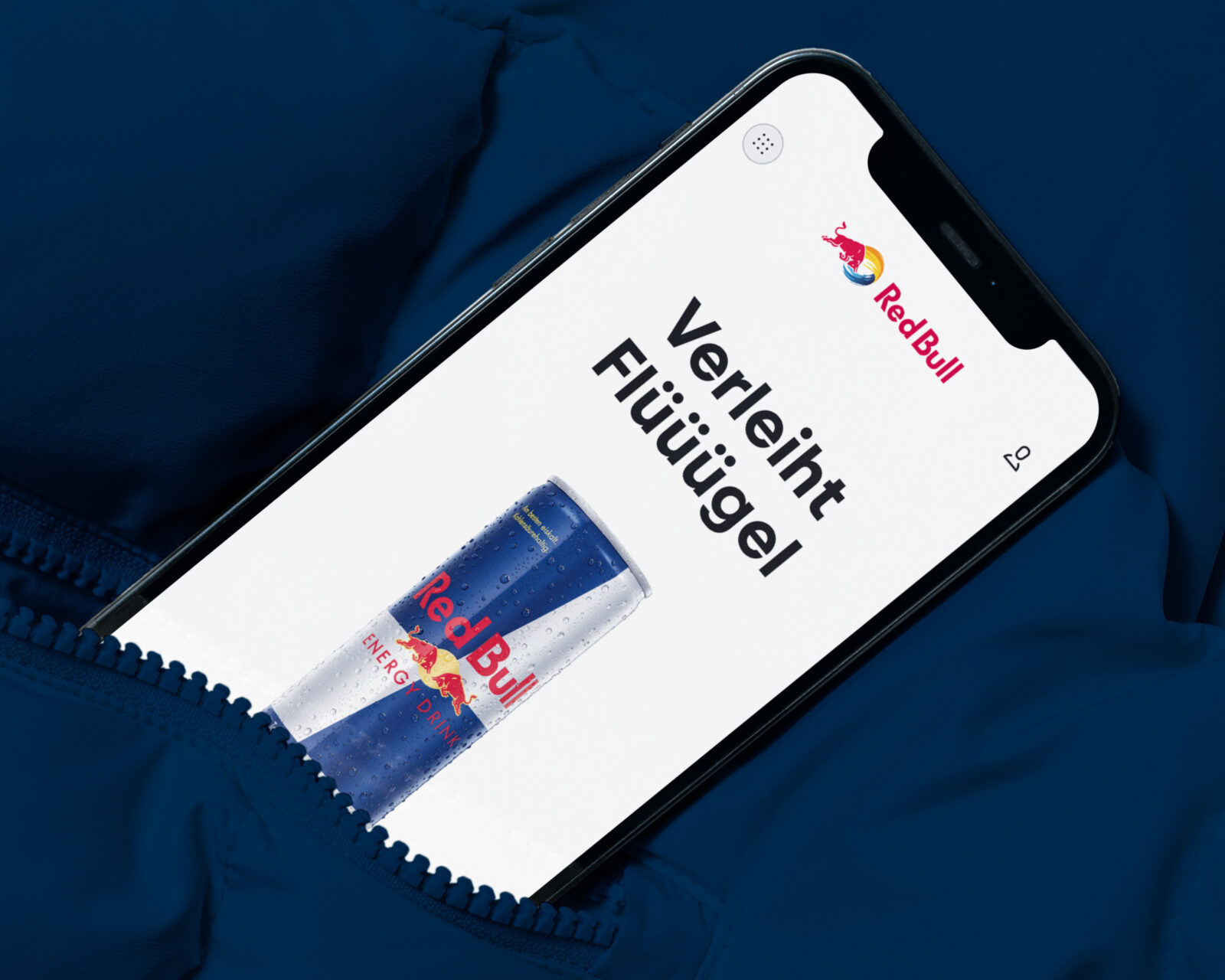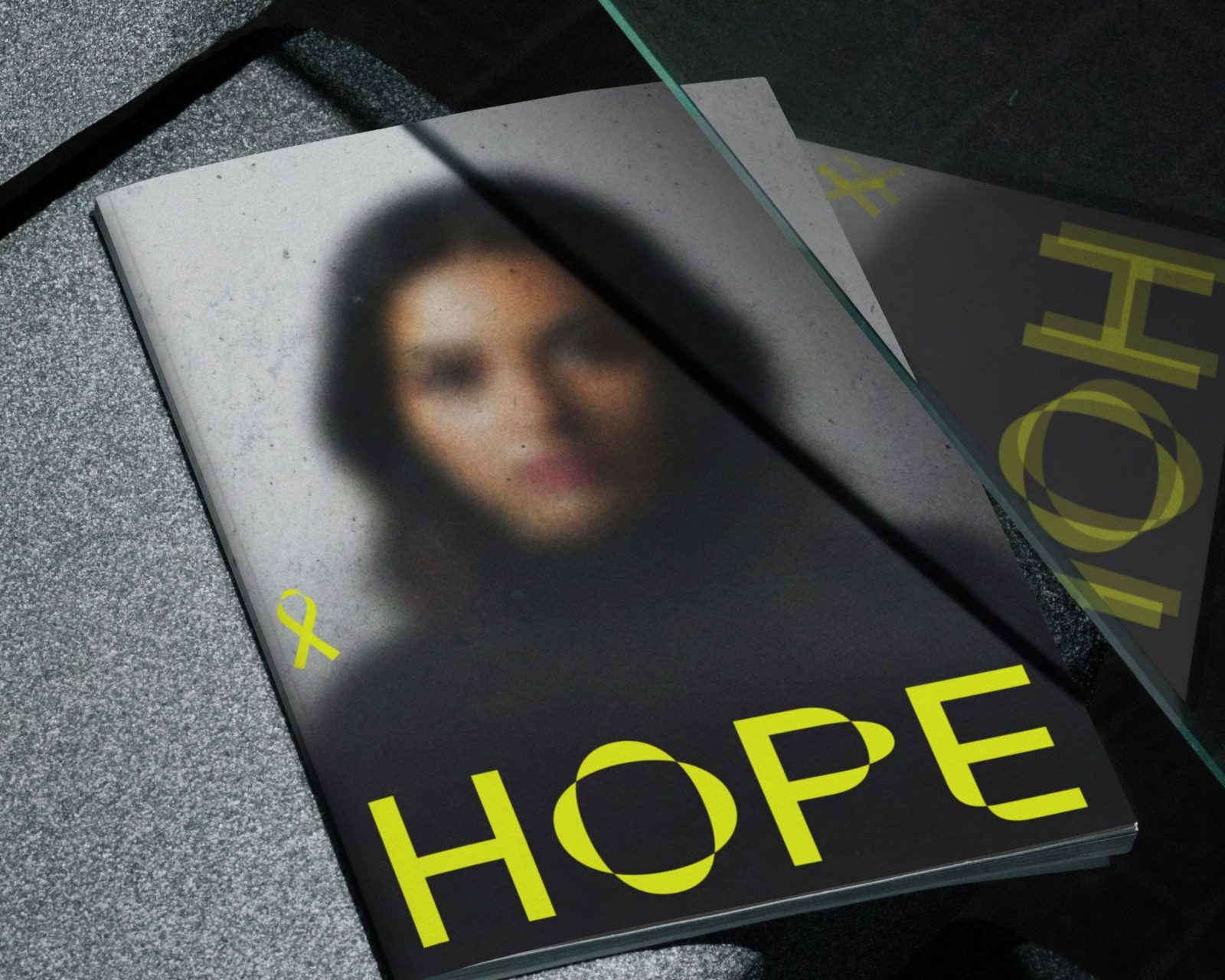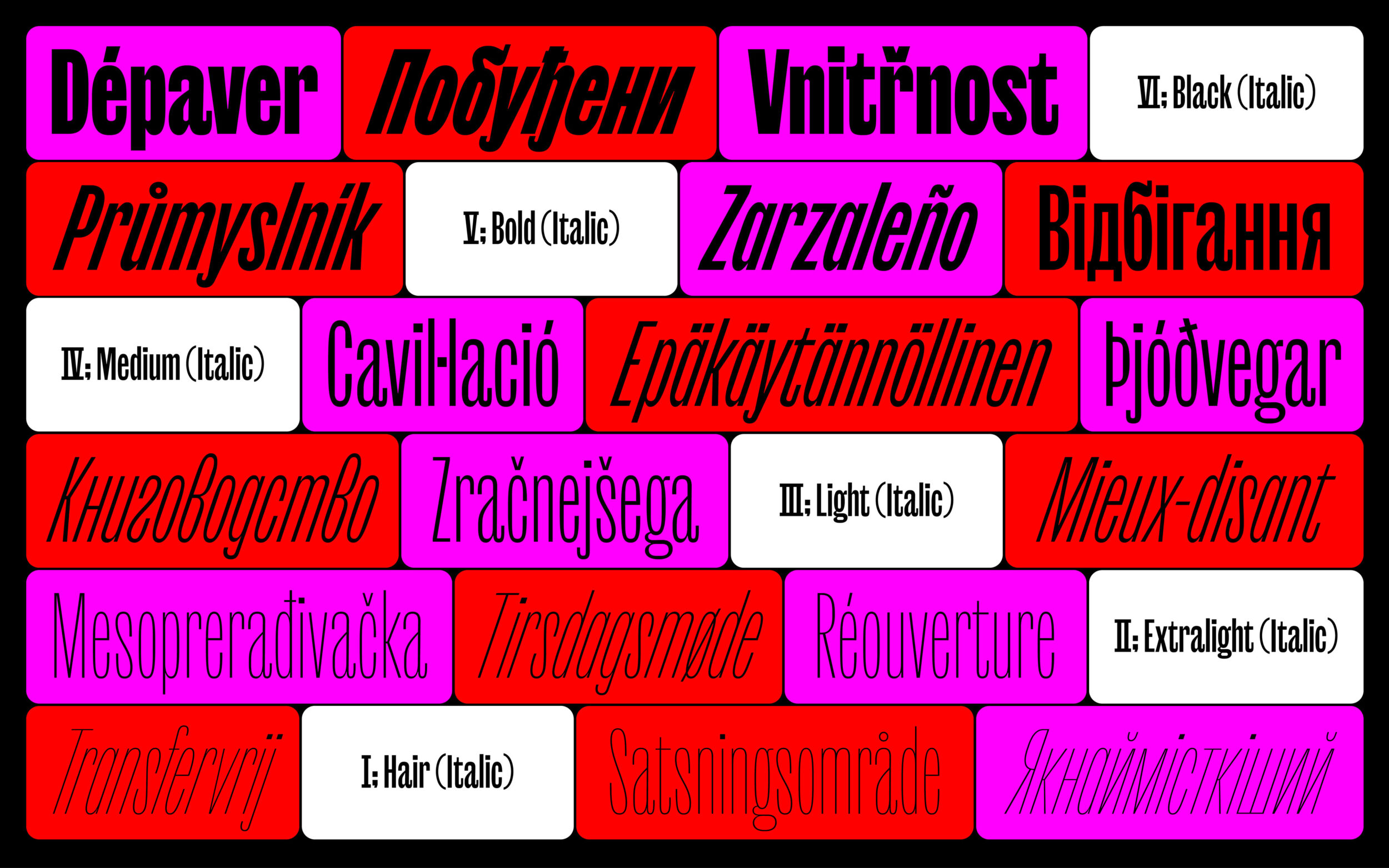
Wir sind TypeMates, eine unkomplizierte Font Foundry mit Expertise für Schrift, einer vielfältigen Font Collection und maßgeschneiderten Custom Fonts.
Halvar Mono: Feste Breite. Volle Kontrolle.
Schnitte von TypeMates, Natalie, Yaprak
Halvar Stencil, eine flexible Schablonenschrift mit industrieller Attitüde.
Schnitte von Paul Eslage & TypeMates
Halvar: Ein konstruiertes Schriftsystem, das bis in die Extreme reicht.
Schnitte von TypeMates
Gregory Text: Verleiht jedem Wort Charme.
Schnitte von Jakob, Seryozha & George
Netto 🚲🎙👁 klare Formen und raffinierte Icons
Schnitte von Daniel Utz
Weymann Serif: Einmal gelesen. Für immer im Gedächtnis.
Schnitte von Marc Weymann
Cera Pro unterstützt pure Geometrie sowie die lateinischen, Кириллица und Ελληνικά Sprachen.
Schnitte von Jakob Runge